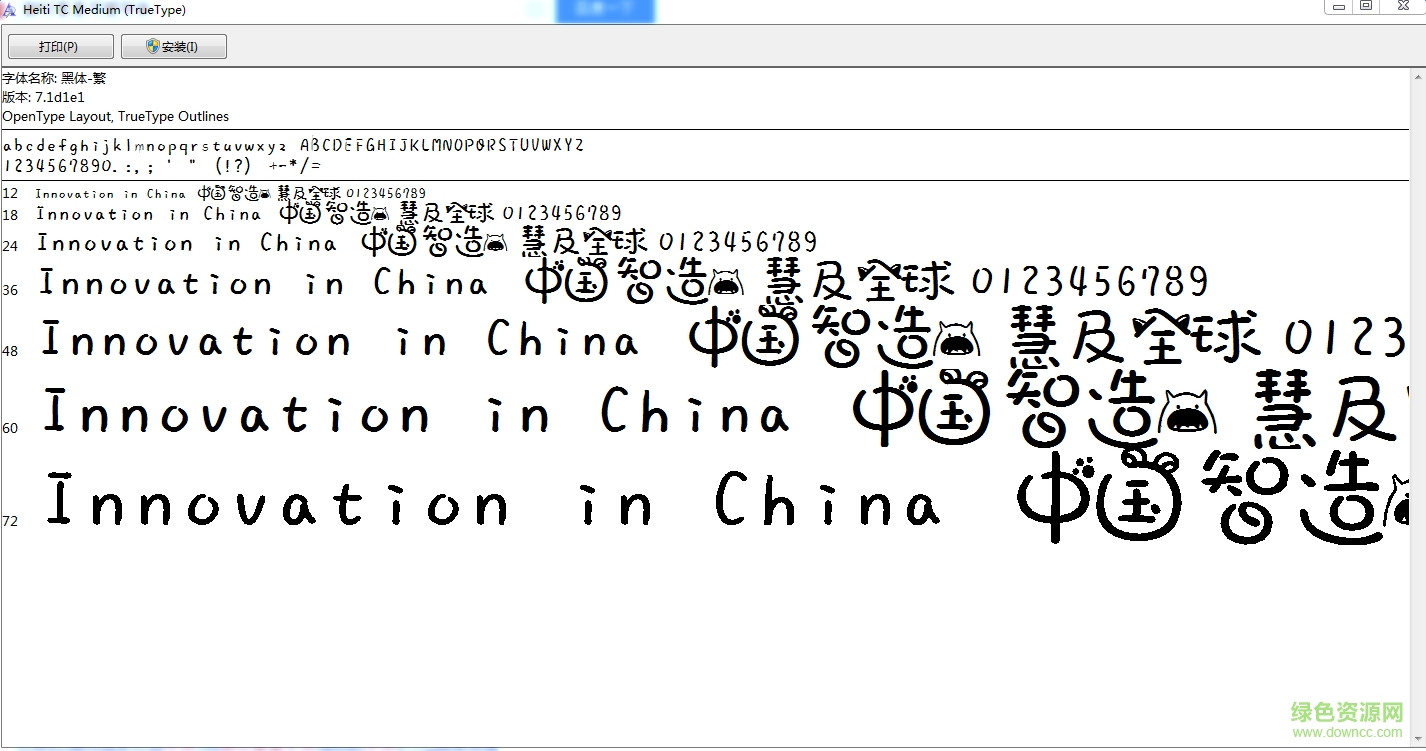
軟件介紹 軟件標簽: 熊貓星星腳印字體 字體 熊貓星星腳印字體是一款不規(guī)則的腳印星星可愛字體,該字體自帶腳印和星星效果,在生活中不常用到,但用在文案設計或平面設計中能讓文字更加生動有趣,喜歡的小伙伴快來綠色資源網(wǎng)下載吧!字體安裝方法方法一:控制面板/字體/文件/安裝新字體;方法二:直接將字體復制到C:\WINDOWS\Fonts。方法三:針對win7系統(tǒng),用戶只需選中字體右鍵安裝即可。注意事項本站所有字體資源僅供個人學習與參考,如需商業(yè)使用請到相關官網(wǎng)授權。 軟件截圖 上一張下一張(1 / 1) 安裝詳細截圖 猜你喜歡 貓咪字體 可愛字體 貓咪字體 貓咪字體給人一種親切、隨意、可愛、呆萌的感覺,看到這樣可愛的字體,讓你一下子就感覺輕松!常被適用于設計學行業(yè),歡迎大家來綠色資源網(wǎng)免費下載使用。 查看更多>> 可愛花貓字體 9.06M/中文/10.0/下載 時光女與貓體 6.76M/中文/10.0/下載 腹黑獸人攻體 10.01M/中文/10.0/下載 貓仔好萌個性字體 7.09M/中文/10.0/下載 小小的貓咪體 9.05M/中文/10.0/下載 腳印星星可愛字體 10.74M/中文/10.0/下載 可愛字體 可愛字體一般都以卡通、秀氣、柔美、女性、兒童等為主調,之前有很多網(wǎng)友都在尋找可愛的字體有哪些?今天由綠色資源網(wǎng)小編為大家分享數(shù)十款可愛中文字體打包下載,每款字體都有其可愛之處,感興趣的朋友歡迎來綠色資源網(wǎng)下載體驗! 查看更多>> 腳印星星可愛字體 10.74M/中文/10.0/下載 漢儀pp體簡 1.70M/中文/5.0/ttf版下載 漢儀黛玉體簡 2.77M/中文/10.0/免費版下載 漢儀晨妹子 5.55M/中文/7.5/簡體免費版下載 可愛心形字體 6.39M/中文/3.6/免費版下載 天使萌貓字體 8.66M/中文/8.5/下載 其他版本下載 標題 大小 更新日期 下載 華康超可愛電子雜志字體打包 40款 36.77M 2019-05-29 下載 美圖秀秀字體閃字素材包 6.90M 2019-06-10 下載 可愛心形字體 免費版 6.39M 2016-03-14 下載 兒童可愛 4.62M 2017-04-25 下載 漢儀可愛字體打包 14款 41.20M 2019-02-27 下載 下載地址 電腦版 腳印星星可愛字體 點擊報錯 軟件無法下載或下載后無法使用,請點擊報錯,謝謝! 關閉報錯反饋 請描述您所遇到的錯誤,我們將盡快予以修正,謝謝! *必填項,請輸入內容 本類最新 dreamweaver字體庫 首爾南山體字體 v1.06 官方版 潮字社風云簡ttf 潮字社凌渡鯤鵬簡體字體 潮字社曾玉波手書簡字體 微博慧心字體 相關文章 Photoshop字體安裝使用方法和技巧 如何解決“無法新增字體”問題 Win 7系統(tǒng)安裝字體方法 網(wǎng)頁字體大小設置方法 怎么改網(wǎng)頁字體大小 在Linux系統(tǒng)中安裝字體的幾種方法 windows7字體顯示問題:打開某些程序的時候顯示的是亂碼 用戶評論 熱門評論 最新評論 發(fā)表評論 查看所有評論(0) 昵稱: 請不要評論無意義或臟話,我們所有評論會有人工審核. 字數(shù): 0/500 (您的評論需要經(jīng)過審核才能顯示)